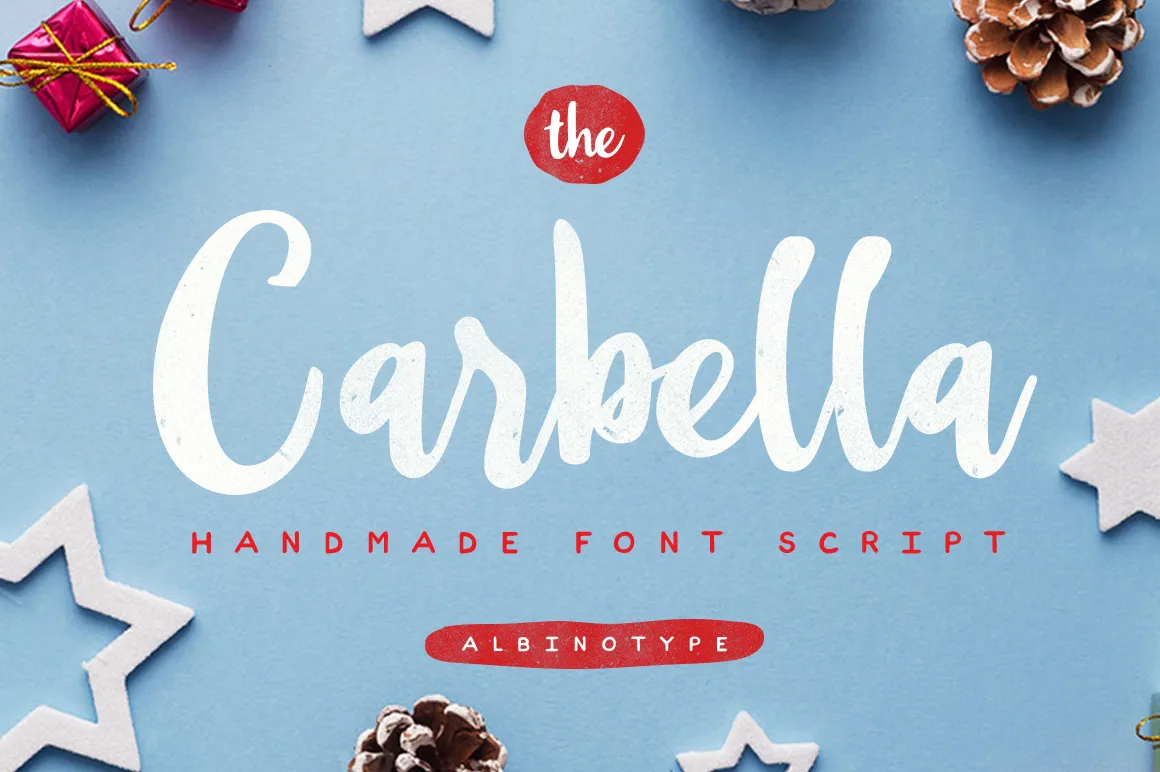
The Carbella Script Font – Fonte Grátis
The Carbella Script Font – Download Grátis
The Carbella Script Font
Aqui está uma versão em português do Brasil das duas linhas curtos para a descrição do download da fonte “The Carbella Script Font”, focando nas informações específicas sem adicionar detalhes fora do texto original: Um belo presente para hoje é um elegante tipo de escrita. A Carbella é um trabalho que resultou inteiramente da escrita com caneta d’água líquida. Possui uma característica natural, perfeita tanto para convites, assinaturas, blogs, mídias sociais, cartões de negócios, como também para marcas de produtos e marcas de marca. Esta fonte Brush é um verdadeiro luxo para designers que procuram manter a autenticidade da escrita com uma aparência sofisticada. Suas linhas fluidas e o aspecto natural permitem que você personalize suas criações de maneira única, conferindo-lhes um toque autêntico sem comprometer a qualidade moderna e elegante do design.